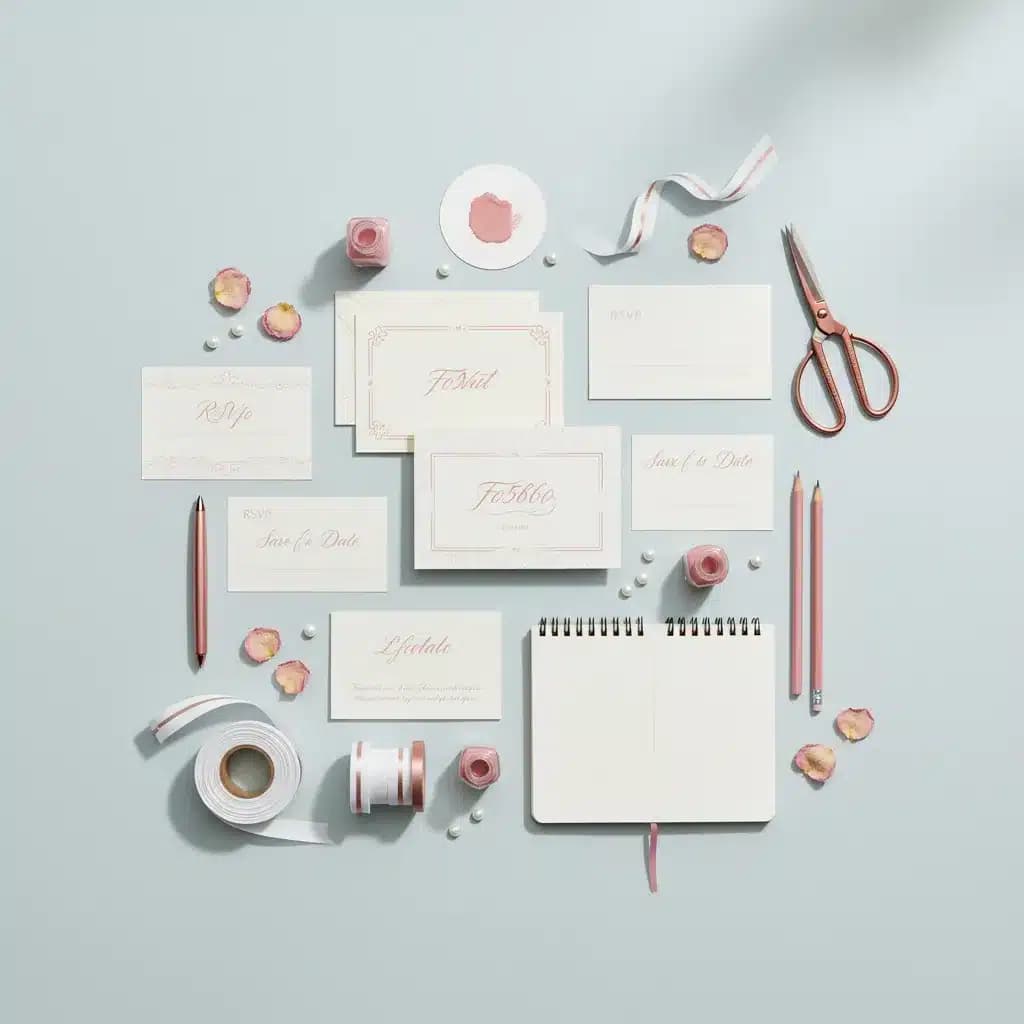
בחירת פונטים לעיצוב נירות חתונה היא החלטה קריטית שמשפיעה על האופי הכללי של האירוע ועל הרושם הראשוני שהזוג משאיר על האורחים. הטיפוגרפיה בהזמנה לחתונה אינה רק אמצעי להעברת מידע – היא חלק בלתי נפרד מהסיפור החזותי של האירוע, משדרת את הסגנון הכללי ויוצרת ציפייה לאירוע עצמו. מעצבים גרפיים ואולמות אירועים המבינים את העקרונות הטיפוגרפיים יכולים ליצור נירות חתונה שבאמת בולטים ונזכרים.
המדריך הזה מיועד למעצבים גרפיים, מעצבי ווב וסטודיו לעיצוב גרפי המעוניינים להעמיק את הידע שלהם בבחירת פונטים מתאימים לנירות חתונה. נבחן את הסוגים השונים של פונטים, עקרונות השילוב ביניהם, והדרכים ליצור היררכיה טיפוגרפית ברורה ואלגנטית.
פונטים לעיצוב נירות חתונה מחולקים לארבע קטגוריות עיקריות, כאשר כל אחת משדרת אופי ותחושה שונים. פונטים קליגרפיים וסקריפט הם הבחירה הפופולרית ביותר לשמות הזוג, משדרים רומנטיקה, אלגנטיות ואופי אישי. לעיצובים המחפשים אופי רומנטי מיוחד, פונט אליאנה הוא פונט סקריפט קליגרפי דו-לשוני המתאים במיוחד לכותרות ולארועים.
פונטים סריפיים קלאסיים משדרים מסורתיות, רצינות ויוקרה, והם מתאימים במיוחד לפרטי האירוע ולטקסטים הארוכים יותר. פונטים אלה קריאים בגדלים קטנים ומעניקים לעיצוב תחושה של עמידות וזמניות. לעיצובים עם אופי עתיק או תנכ"י, פונט שושן הוא פונט מעוטר קליגרפי המתאים לכותרות דיספליי ומוסיף אופי מיוחד להזמנה.
פונטים Sans Serif מודרניים מתאימים לזוגות המחפשים מראה עכשווי, מינימליסטי ונקי. פונטים אלה משדרים פשטות ואלגנטיות מודרנית, ומתאימים במיוחד לחתונות בסגנון אורבני או מינימליסטי.
שילוב נכון של פונטים בנירות חתונה הוא אמנות שדורשת הבנה של עקרונות טיפוגרפיים בסיסיים. העיקרון המרכזי הוא יצירת היררכיה ברורה – כל רכיב בהזמנה צריך להיות מזוהה מיידית לפי חשיבותו. שמות הזוג הם בדרך כלל הרכיב הדומיננטי ביותר, ולכן ראויים לפונט בולט – לרוב קליגרפי או דקורטיבי. פרטי האירוע (תאריך, שעה, מקום) צריכים להיות קריאים בקלות, ולכן מתאימים לפונט סריף או sans serif פשוט יותר.
כלל הניגוד והשלמה הוא קריטי – פונטים שונים צריכים להשלים זה את זה, לא להתחרות. שילוב קלאסי הוא פונט קליגרפי עדין לשמות הזוג עם פונט סריף פשוט לפרטים. לדוגמה, שילוב של פונט מיה – פונט סקריפט קליגרפי מעוטר המתאים לכותרות – עם פונט טקסט רץ פשוט יותר יוצר איזון אלגנטי.
מספר הפונטים בעיצוב אחד צריך להיות מוגבל – שני עד שלושה פונטים לכל היותר. יותר מכך יוצר תחושה של עומס ויזואלי וחוסר מקצועיות. כאשר משתמשים בשני פונטים בלבד, הניגוד ביניהם צריך להיות ברור – למשל, קליגרפי מול sans serif, או סריף כבד מול סריף דק.
אחת הטעויות השכיחות ביותר היא שימוש בפונט קליגרפי מורכב מדי שקשה לקריאה. פונטים קליגרפיים צריכים להיות דקורטיביים אך עדיין קריאים – במיוחד כאשר מדובר בשמות. אורחים צריכים להבין מיד מי מזמין אותם לאירוע. בדיקת קריאות בגדלים שונים היא הכרחית לפני אישור העיצוב הסופי.
התעלמות מהיררכיה ויזואלית היא בעיה נפוצה נוספת. כאשר כל הטקסט באותו גודל ומשקל, האורח לא יודע מה חשוב יותר. יש ליצור הבדלים ברורים בין רמות המידע השונות – שמות הזוג בולטים ביותר, אחריהם פרטי המקום והזמן, ולבסוף פרטים משניים כמו הוראות הגעה או קוד לבוש.
טעות נוספת היא אי-התאמה בין סגנון הפונט לאופי האירוע. חתונה פורמלית בגן אירועים מסורתי דורשת פונטים קלאסיים ומעודנים, בעוד חתונה אורבנית בלופט יכולה לאפשר פונטים מודרניים ומינימליסטיים יותר. השימוש בפונטים שלא מתאימים לאופי האירוע יוצר דיסוננס ויזואלי ומבלבל את האורחים לגבי הציפיות מהאירוע.
נקודות מפתח למניעת טעויות:שילוב קלאסי ואלגנטי הוא פונט קליגרפי עדין לשמות + סריף מסורתי לפרטים. לדוגמה, שימוש בפונט סקריפט דק ואלגנטי לשמות הזוג בגודל 32pt, בשילוב עם פונט סריף קלאסי כמו Garamond או Baskerville לפרטי האירוע בגודל 11pt, יוצר איזון מושלם בין רומנטיקה למסורתיות. שילוב זה מתאים במיוחד לחתונות פורמליות באולמות מסורתיים או בגנים היסטוריים.
שילוב מודרני ומינימליסטי הוא sans serif דק לשמות + sans serif בולד לפרטים. שימוש באותה משפחת פונט במשקלים שונים יוצר לכידות ויזואלית תוך שמירה על היררכיה ברורה. לדוגמה, משפחת הפונטים Helvetica Neue או Montserrat במשקלים Light (200) לשמות ו-SemiBold (600) לפרטים מעניקה מראה עכשווי ונקי.
לעיצובים בעלי אופי מיוחד או תנכ"י, פונט תטואן הוא פונט סריף קליגרפי בסגנון סת"ם המתאים לחתונות עם אופי מסורתי או מרוקאי. שילובו עם פונט sans serif פשוט לפרטים המשניים יוצר ניגוד מעניין בין מסורת למודרניות.
מומלץ להגביל את מספר הפונטים לשניים-שלושה לכל היותר. פונט אחד לשמות הזוג (קליגרפי או דקורטיבי), פונט שני לפרטי האירוע (סריף או sans serif קריא), ואופציונלי פונט שלישי לפרטים משניים. שימוש ביותר מדי פונטים יוצר עומס ויזואלי ומפחית מהמקצועיות של העיצוב.
פונטים קליגרפיים מתאימים במיוחד לחתונות רומנטיות, קלאסיות ופורמליות. עם זאת, לחתונות מודרניות, מינימליסטיות או אורבניות, פונטים sans serif נקיים עשויים להתאים יותר. החשוב הוא שהפונט ישקף את אופי הזוג ואת הסגנון הכללי של האירוע. תמיד כדאי לבחור קריאות על פני דקורטיביות יתרה.
לטקסט גוף (פרטי האירוע, כתובת, הוראות) מומלץ גודל מינימלי של 10-11pt. לכותרות משניות 14-16pt, ולשמות הזוג 24-36pt. חשוב לזכור שפונטים שונים נראים בגדלים שונים – פונט דק עשוי להיראות קטן יותר מפונט בולד באותו גודל נומינלי. תמיד הדפיסו דוגמה בגודל אמיתי לבדיקה לפני הפקה סופית.
בחירת פונטים לעיצוב נירות חתונה היא החלטה שמשלבת אסתטיקה, פונקציונליות ואופי אישי. העקרונות המרכזיים שסקרנו – יצירת היררכיה ברורה, שילוב הרמוני בין פונטים משלימים, והגבלת מספר הפונטים – הם הבסיס לעיצוב מקצועי ואפקטיבי. פונטים לעיצוב נירות חתונה צריכים תמיד לשרת את המטרה העיקרית: להעביר מידע בצורה ברורה תוך יצירת רושם ראשוני חיובי ובלתי נשכח.
מעצבים גרפיים ואולמות אירועים שמבינים את העוצמה של טיפוגרפיה נכונה יכולים להעניק לזוגות הזמנות שבאמת משקפות את האופי שלהם ויוצרות ציפייה לאירוע. השקעת זמן בבחירת פונטים מתאימים, בדיקת קריאות בגדלים שונים, והתייעצות עם מדפיס מקצועי הם צעדים הכרחיים לתוצאה מושלמת. פונטים לעיצוב נירות חתונה הם לא רק כלי טכני – הם חלק בלתי נפרד מהסיפור החזותי של היום הגדול.